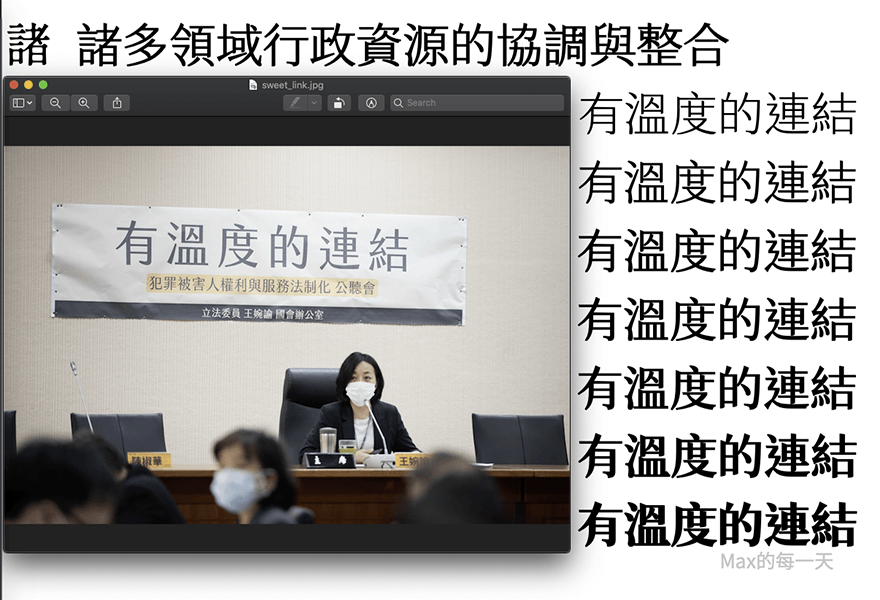
字体名称: 狮尾四季春
狮尾四季春
狮尾四季春字体下载SweiSpring
Max前几天看到一篇文章,在讲有温度的连结,然后看到横幅上的字体,可能是金萱的字体,非常特别,这款字体把黑体和宋体结合了在一起,看上去非常好看。于是Max通过程序修改思源宋体,把思源宋体里的右边三角形衬线拿掉,并帮字体取名为狮尾四季春。虽然不太完美,但是看上去感觉还不错。
狮尾四季春是基于思源宋体拔三角形改造,看上去会更加简明现代化,版面效果清新轻快。缺点是比较轻,横笔明显极细。和思源宋体一样,狮尾四季春支持简体中文、繁体中文、韩文与日文,并且支持6个字重。